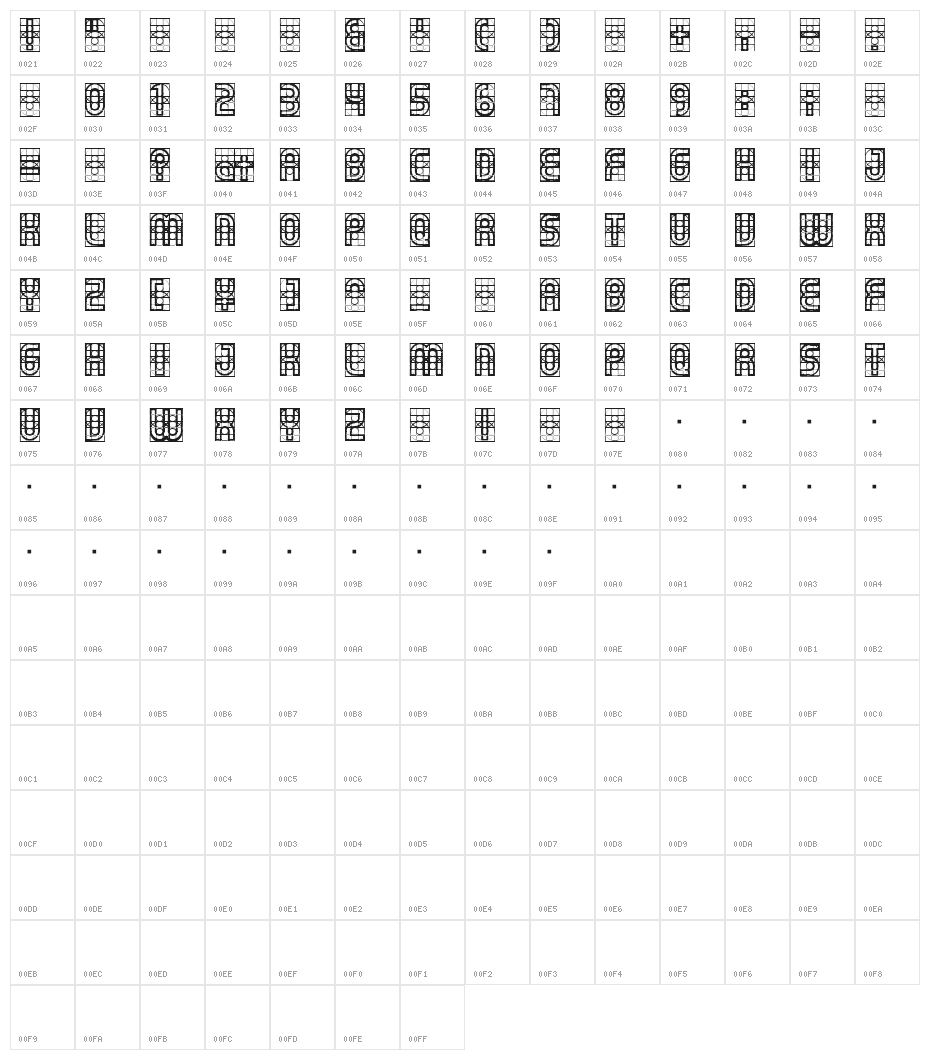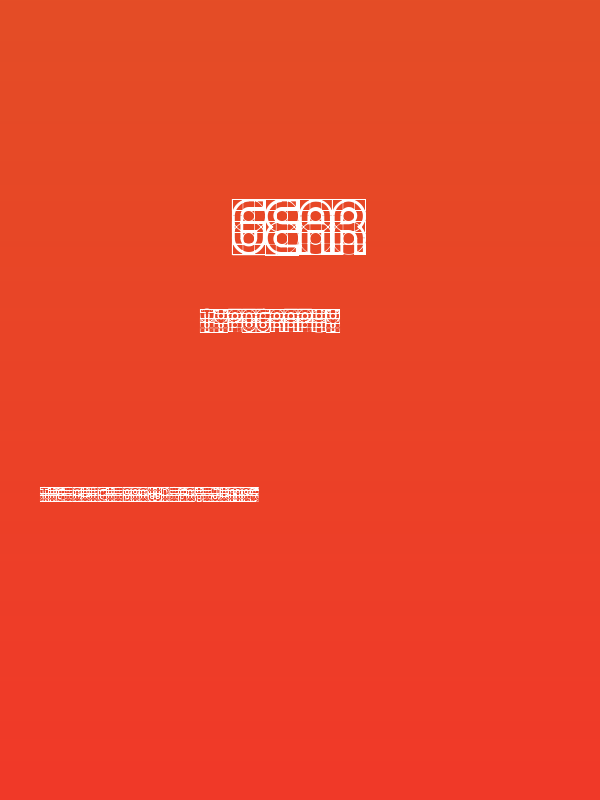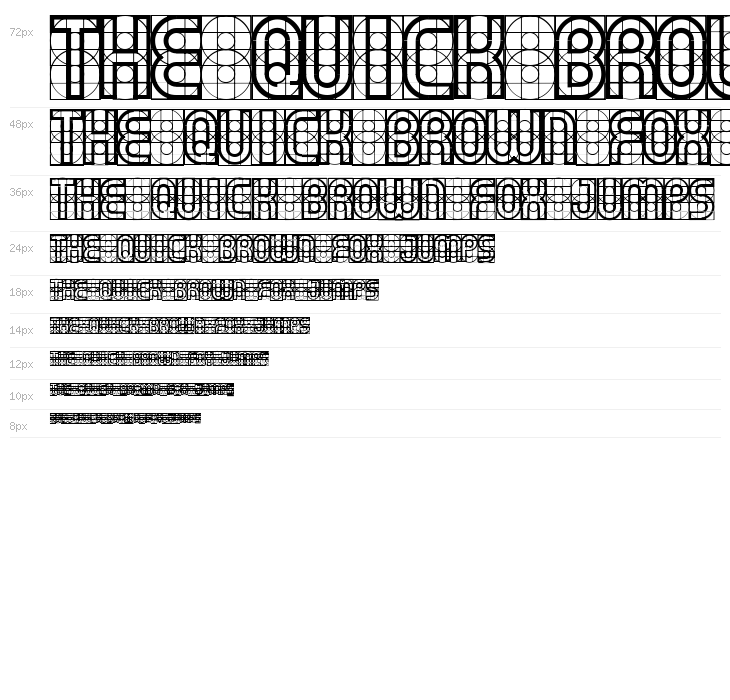
Gear Font
| Anwendungsfall | Logos, Headlines, Posters |
| Vorgeschlagene Projekte | Ideal for technology branding, modern art posters, and innovative product packaging. |